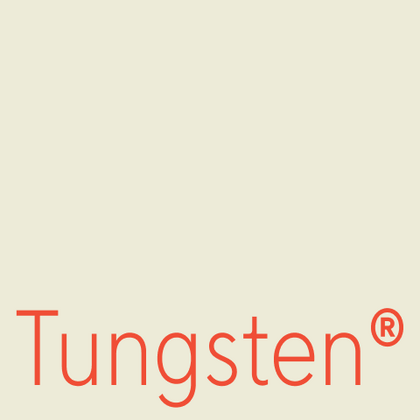
Шрифты похожие на Tungsten
Шрифтовая альтернатива: Tungsten
TT Commons™ Pro — TT Коммонс Про
TT Hoves Pro — ТТ Ховс Про
Произносится «ТТ Ховс Про». «Hoves» — производное слово от horizontal (с английского «горизонтальный») и vertical (с английского «вертикальный»). «Pro» произносится как «про», и является разговорным сокращением слова «профессиональный». Буквы «TT» являются аббревиатурой названия компании.
TT Supermolot Neue — ТТ Супермолот Нью
Произносится «ТТ Супермолот Нью». «Supermolot» — производное слово от super (с английского «супер») и molot (транслитерация слова «молот»). «Neue» — в переводе c немецкого «новый». Буквы «TT» являются аббревиатурой названия компании.
TT Runs — ТТ Ранс
Произносится «ТТ Ранс». «Runs» — производное слово от run, в переводе с английского «бег». Буквы «TT» являются аббревиатурой названия компании
TT Bluescreens Pro — ТТ Блюскринс Про
Произносится «ТТ Блюскринс Про». «Bluescreens» — производное слово от двух слов blue (с английского «синий») и screen (с английского «экран»). «Pro» произносится как «про», и является разговорным сокращением слова «профессиональный». Буквы «TT» являются аббревиатурой названия компании.
TT Frantz — ТТ Франтц
Произносится «ТТ Франтц». «Frantz» — имя собственное немецкого происхождения. Буквы «TT» являются аббревиатурой названия компании.
TT Modernoir — ТТ Модернуар
Произносится «ТТ Модернуар». «Modernoir» — производное слово от moderne (с французского «современный») и noir (с французского «чёрный»). Буквы «TT» являются аббревиатурой названия компании.
TT Octosquares — ТТ Октосквэрс
Произносится «ТТ Октосквэрс». «Octos» — производное слово от octa (с греческого «восемь») и «squares» — производное от square (с английского «квадрат»). Буквы «TT» являются аббревиатурой названия компании.
TT Lakes Neue — ТТ Лэйкс Нью
Произносится «ТТ Лэйкс Нью». «Lakes» — производное слово от lake, в переводе с английского «озеро», «Neue» — в переводе c немецкого «новый». Буквы «TT» являются аббревиатурой названия компании.
TT Polls — ТТ Поллс
Произносится «ТТ Поллс». «Polls» — производное слово от poll, в переводе с английского языка «голосование», отсылка к голосованиям в спортивных соревнованиях. Буквы «TT» являются аббревиатурой названия компании.
TT Octas — ТТ Октас
Произносится «ТТ Октас». «Octas» — производное слово от octa, в переводе с греческого «восемь». Буквы «TT» являются аббревиатурой названия компании.
TT Bricks — ТТ Брикс
Произносится «ТТ Брикс». «Bricks» — производное слово от brick, в переводе с английского «кирпич». Буквы «TT» являются аббревиатурой названия компании.
Шрифты похожие на Tungsten
Если вам нравится смелый и стильный Шрифт Tungsten®, загляните в нашу коллекцию. В TypeType есть отличные альтернативные шрифты. Они отлично смотрятся в логотипах, рекламе и заголовках, при этом поддерживают кириллицу. Выбирайте из нескольких вариантов и создавайте запоминающийся дизайн.
Если вы устали от «заезженных» шрифтов и ищете гарнитуры, похожие на Tungsten, ознакомьтесь с нашими лучшими альтернативами Tungsten. Это шрифты, которые имеют близкие характеристики, но в то же время обладают новыми уникальными особенностями дизайна. Например, относятся к той же категории шрифтов, подходят для тех же целей и имеют похожие черты, но отличаются в деталях или пропорциях.
В TypeType вы найдете передовые шрифты, такие как Tungsten и даже лучше: вот несколько замечательных и не столь распространенных альтернатив Tungsten. Используйте этот список высококачественных, выглядящих как Tungsten шрифтов, на свой вкус. Так вы сможете подобрать еще более для вашего проекта подходящий шрифт, расширив выбор, или освежить свой дизайн. Все шрифты, представленные в этой коллекции, доступны в разных форматах и ​​по доступным ценам, поэтому вы сможете найти тот, который соответствует любым потребностям!
Найдите отличную замену Tungsten и попытайтесь имитировать похожее настроение, передать нужное вам ощущение, используя его в своих проектах. Каждый шрифт, представленный на этой странице, является двойником шрифта Tungsten, фактически его полным аналогом.